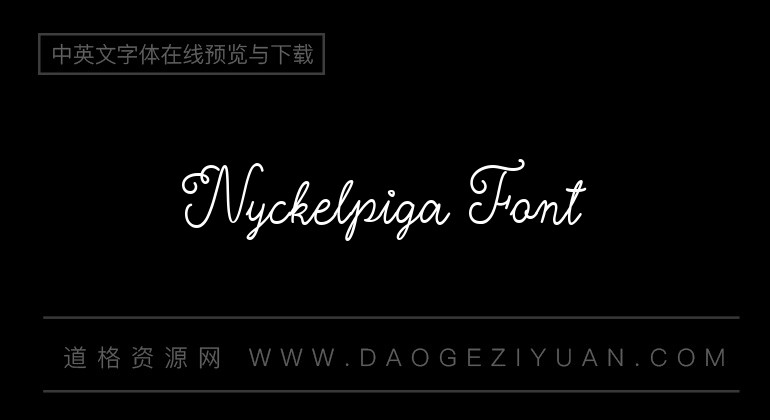
Nyckelpiga Font
Nyckelpiga Font 是一种手写风格的字体,它的特点是字母和数字的线条流畅自然,仿佛是由人手书写而成。该字体的设计者是来自瑞典的 Sune Matras,它的名字“Nyckelpiga”在瑞典语中意为瓢虫。 Nyckelpiga Font 包含了大写字母、小写字母、数字和标点符号,适用于各种设计应用,例如海报、卡片、标志、包装等等。该字体的使用可以让设计作品更具个性和温暖感,与其他传统字体有所不同。
Nyckelpiga Font是一款非常不错的手写艺术字体,具有很好的视觉感,适合于文化类的宣传设计、商业类品牌的广告和产品包装设计以及个性化文字排版等较多场景。